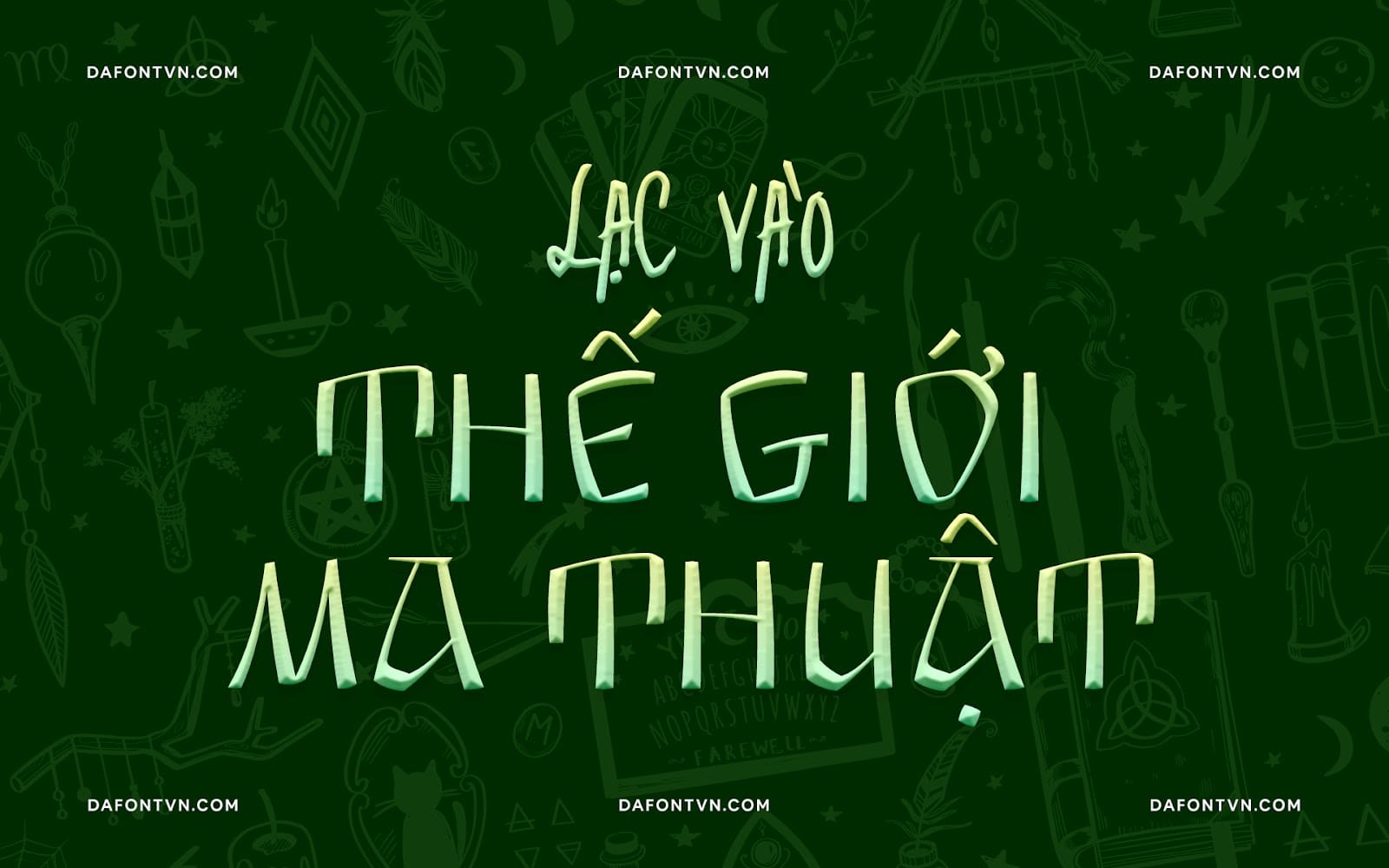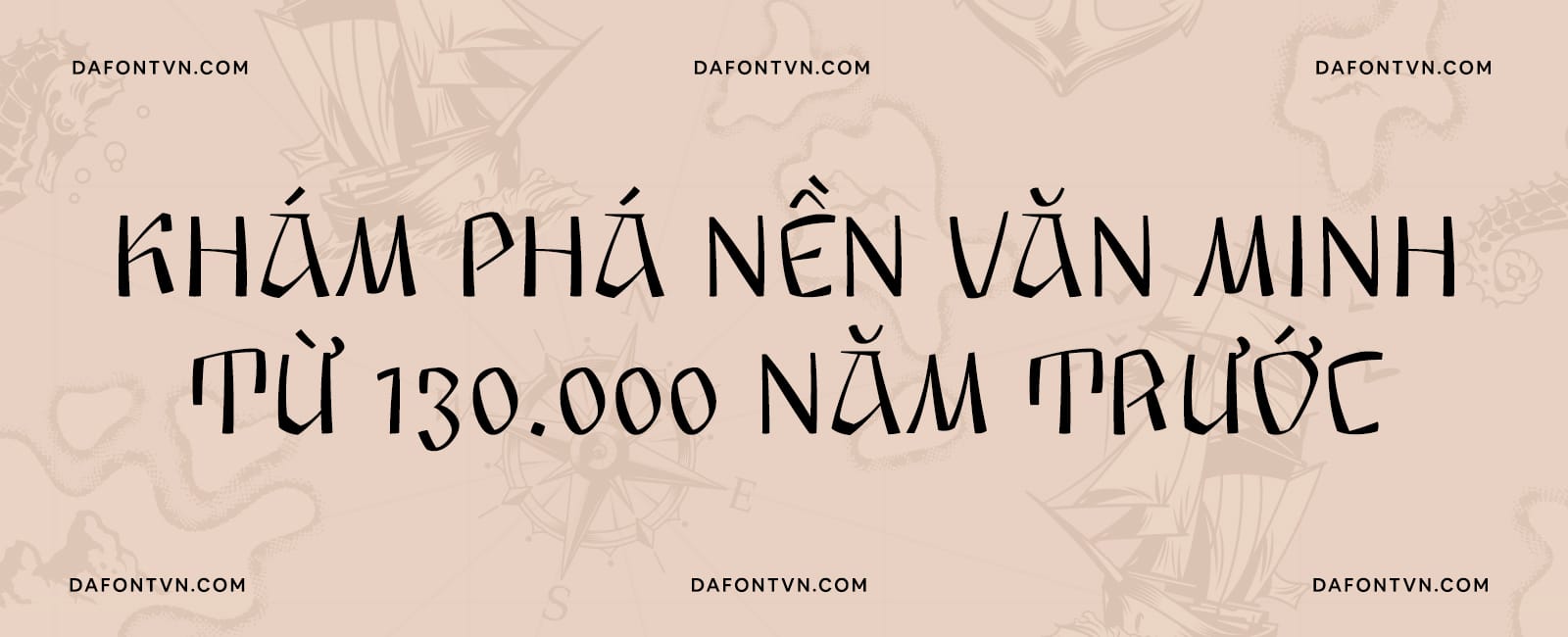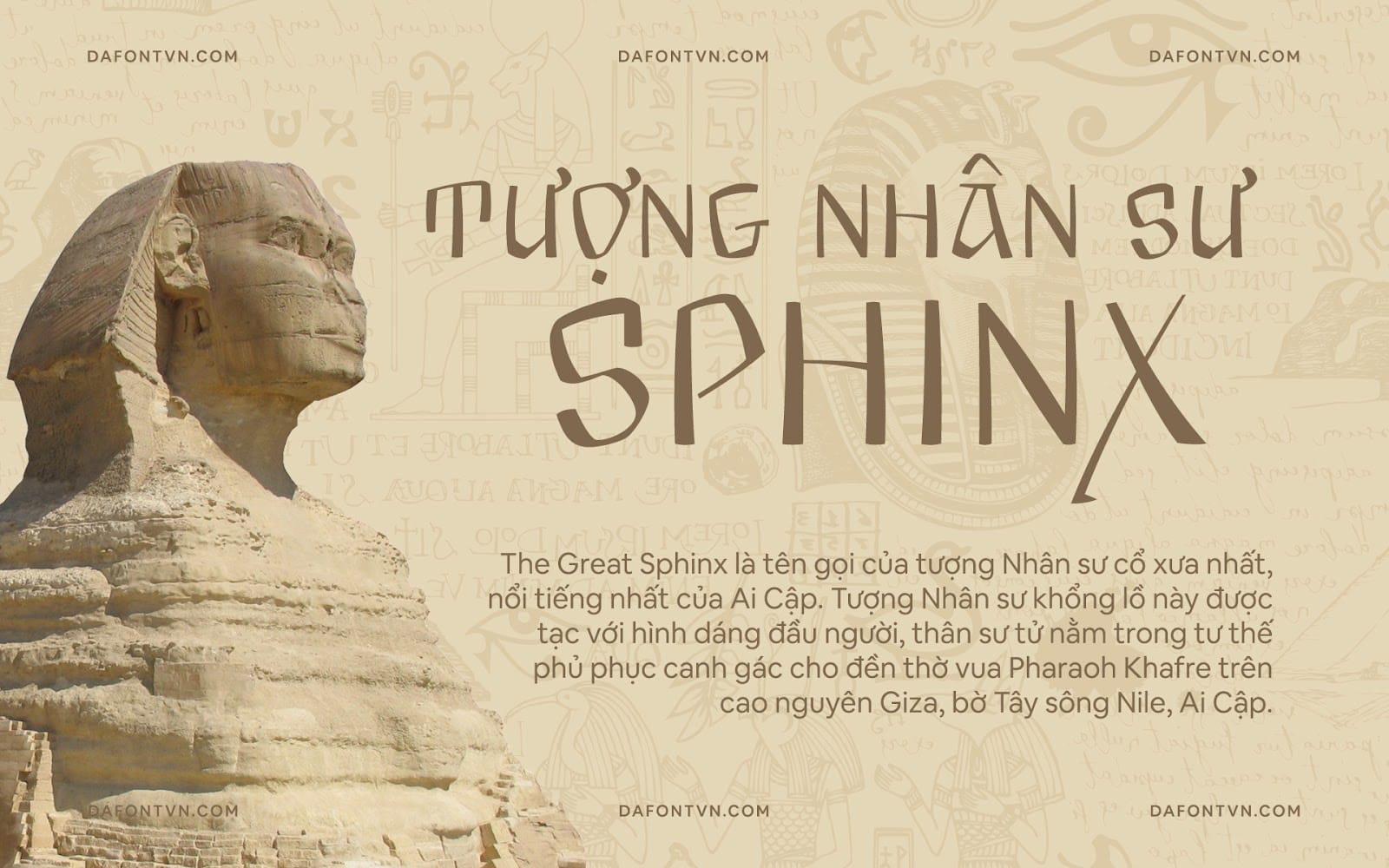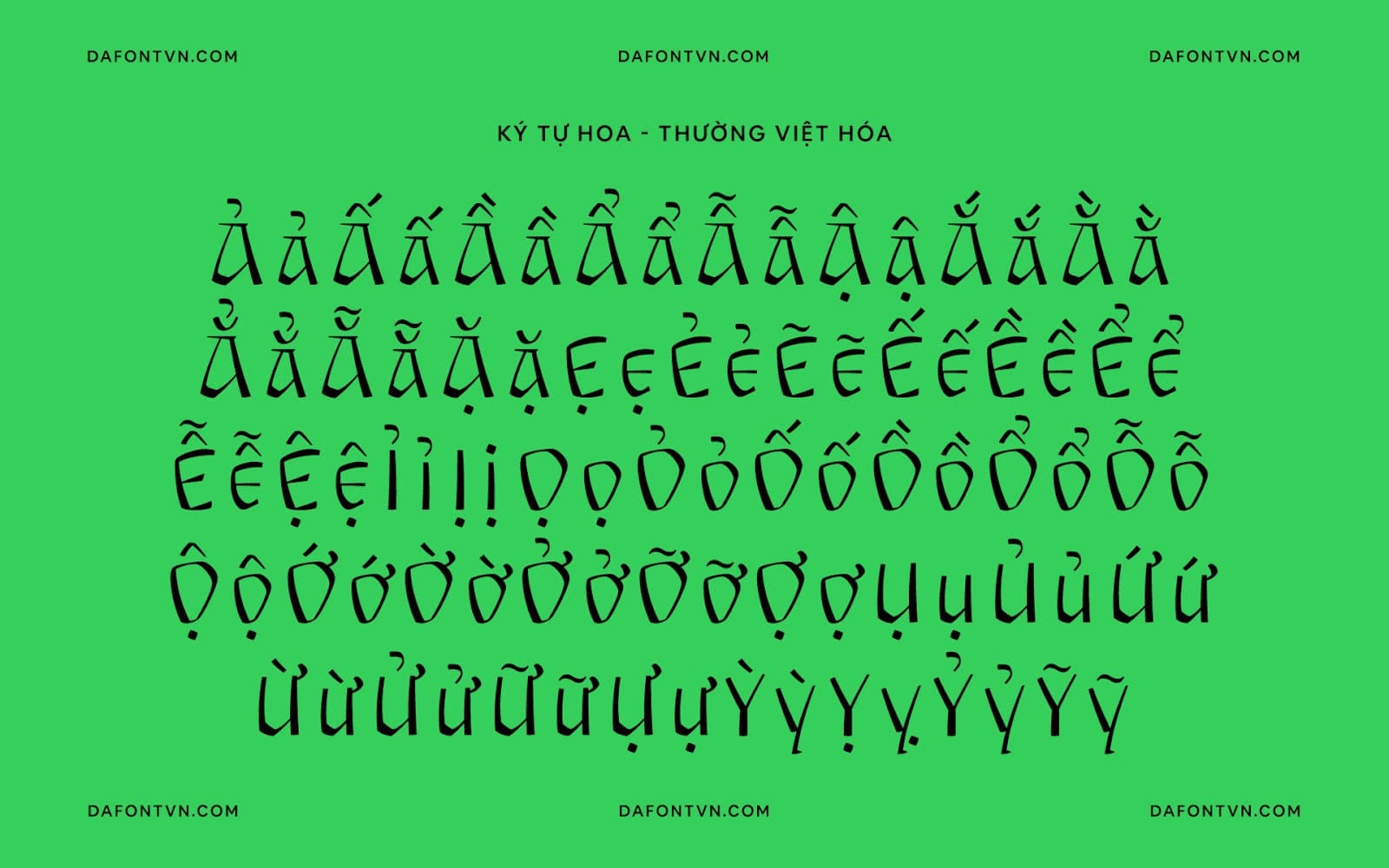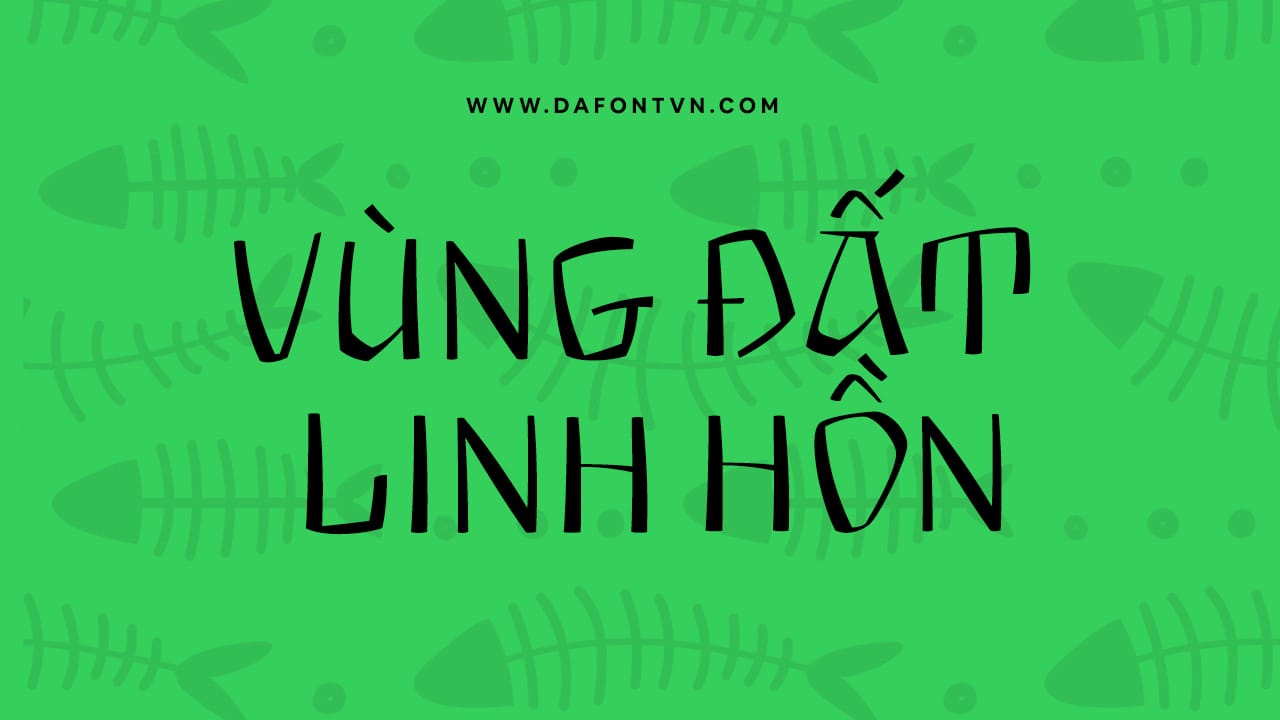
Arkaim là một kiểu chữ Nga mang phong cách cổ xưa, đây là kiểu chữ truyền thống của East-Slavic và GreatRussian. Phong cách này không giống bất kỳ phong cách nào khác trên thế giới. Nó kết hợp sự sang trọng và ngắn gọn, chiều sâu và hiện đại, độc đáo và thú vị.
Phông chữ Arkaim được đặt theo tên của thành phố Slavic-Aryan cổ nằm ở phía nam nước Nga, là biểu tượng của sự cổ xưa cũng như thế giới cổ đại chưa được khám phá. Arkaim không chỉ là địa điểm lịch sử mà còn là nơi chứa đựng sức mạnh tâm linh.
Kiểu chữ Arkaim có nhiều tính năng Opentype giúp tạo ra các bố cục thú vị và độc đáo. Một giải pháp thú vị là sự kết hợp giữa chữ viết hoa và chữ thường. Arkaim chứa các ký tự của tất cả các ngôn ngữ Slavic và châu Âu. Có ký tự phân số, ký tự trên và dưới, và nhiều ký tự khác. Có số thường và số kiểu cũ, cũng như số Slavic. Có tất cả các ký tự lịch sử của bộ chữ cổ Slavic được gọi là Bukvitsa, ngày nay sai lầm gọi là tiếng Cyrillic.
Font Arkaim rất phù hợp để sử dụng trong các thiết kế mang tính cổ xưa hoặc bất kỳ thiết kế nào khác và được hiển thị tốt khi sử dụng ở kích thước lớn đặc biệt khi sử dụng làm tiêu đề.